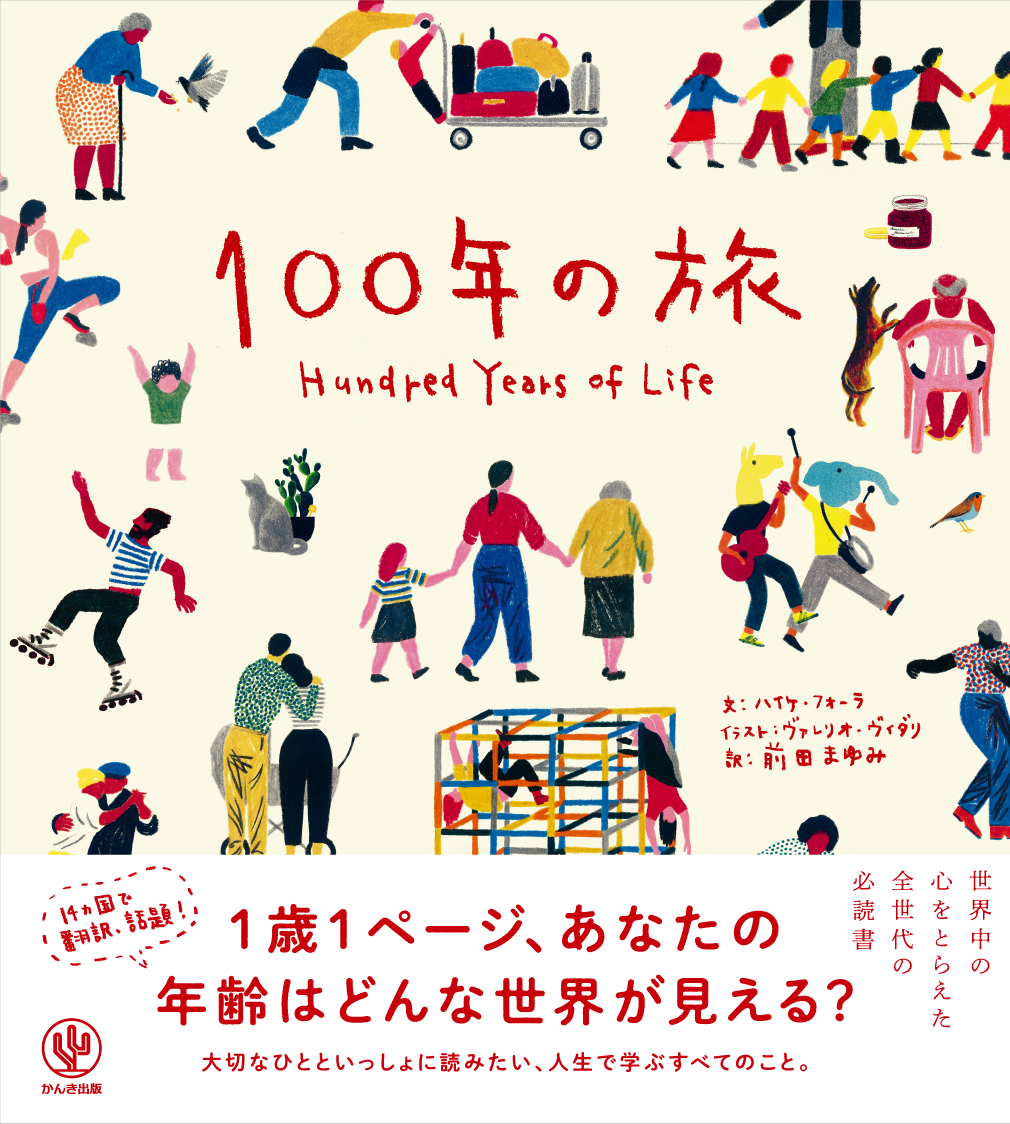
100年の旅
かんき出版は、ハイケ・フォーラ氏著書、ヴァレリオ・ヴィダリ氏イラスト、前田まゆみ訳による、全国の書店員から圧倒的な支持を得た世界中の心をとらえたドイツ絵本で0歳から99歳を描いた「100年の旅」を2020年2月19日より全国の書店・オンライン書店等(一部除く)で発売した。
人生がどうなっているか知りたいですか?すべてが「100年の旅」にあります。
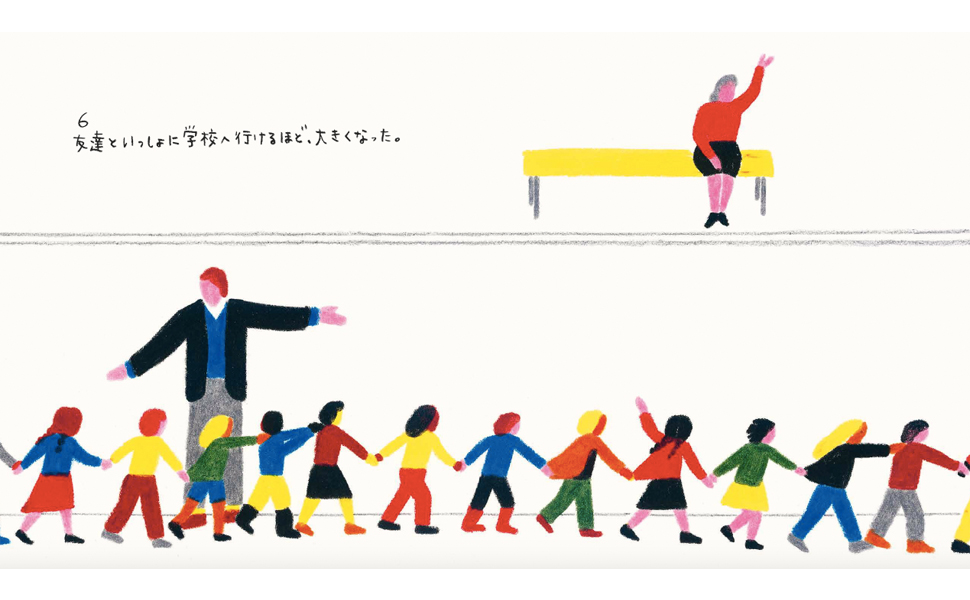
ドイツから世界中の心をとらえ、14カ国で翻訳のベストセラー絵本『100年の旅』の邦訳版が発売となる。1ページごとに1歳ずつ年を重ねていくユニークな構成で、人の一生が1冊に収められている。さまざまなことができるようになり、世界の広さを学ぶ幼少年期、家族が増え、本当に大切なものや幸せとは何かを学ぶ中年期、別れの喪失と時間の儚さ、そして尊さを学ぶ老年期、どの世代にも、そのときどきで大切な学びがあるということを、心に響く言葉と色彩豊かなイラストで描かれている。「100年の旅」はあらゆる世代の人に向けられたもので、家族で一緒にこの本を読むこと、パートナーと一緒に読むことで対話を促し、人生について一緒に考えることにもつながる世代によって感じ方が変わる本。
柔らかい手描き文字は『翻訳できない世界のことば』翻訳者の前田まゆみ氏
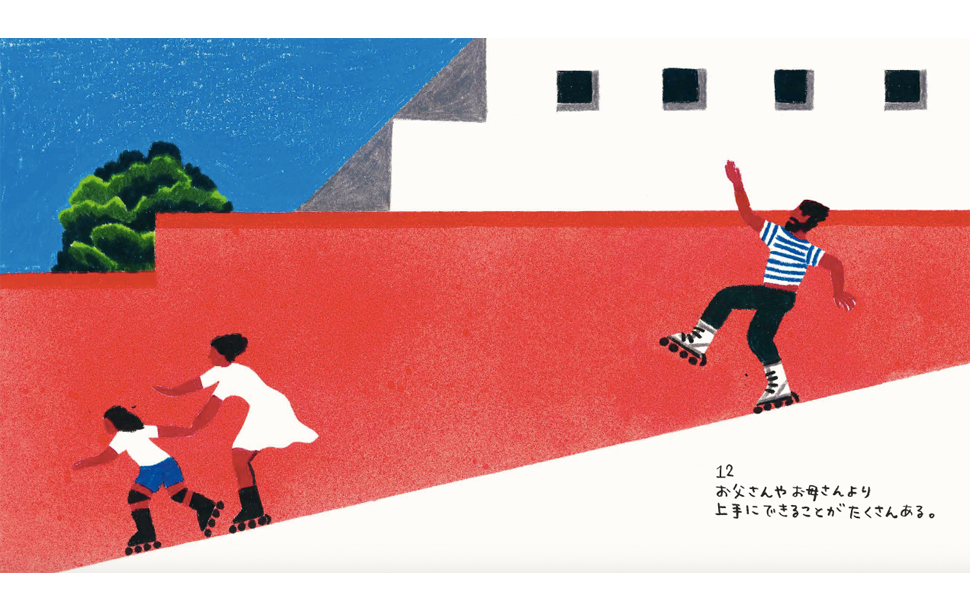
2017年キノベス第1位を受賞した「翻訳できない世界のことば」翻訳者で絵本作家の前田まゆみ氏による、ほっこりする手描き文字で、様々なシーンのプレゼントにもぴったり。
「100年の旅」著者「あとがき」より
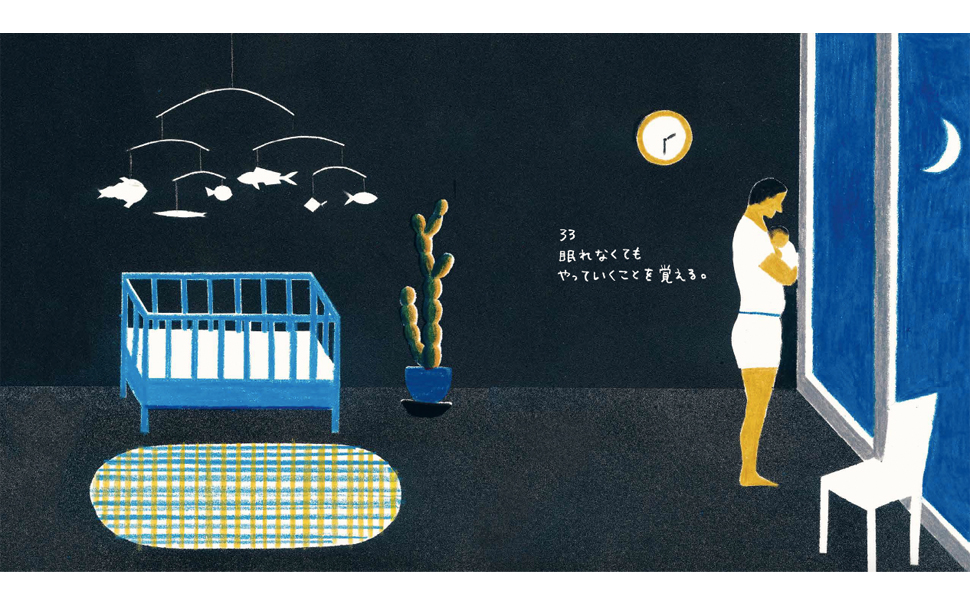
この本のアイデアは、あるとき、ふと生まれました。それは、生後間もない姪っ子が、ミイラのように布にくるまれ、外界に向かってまばたきしているのをはじめて見たときでした。なんて不可思議な旅が、この子を待ち受けていることか! と思ったのです。彼女を待ち受ける素敵なことをうらやましく思う気持ちが半分。でも同時に、今までのさまざまな痛みの記憶から、自分の中につまっている悲しみを思い、同じものがやはり彼女を待ち受けているとも感じました。
悲しいことに、おとなになると私たちは、世界に満ちる驚き、たとえば、連なる山々や満月、そして他者から受ける愛情になんだか慣れてしまい、当たり前に思ってしまうことがあります。それらの気高さを感じ取る心をもう一度取り戻すには、世界を新しい視点で見る必要があるのかもしれません。この本では、人生のそれぞれの局面で、世界の見え方が変わるということを表現できたらと思いました。